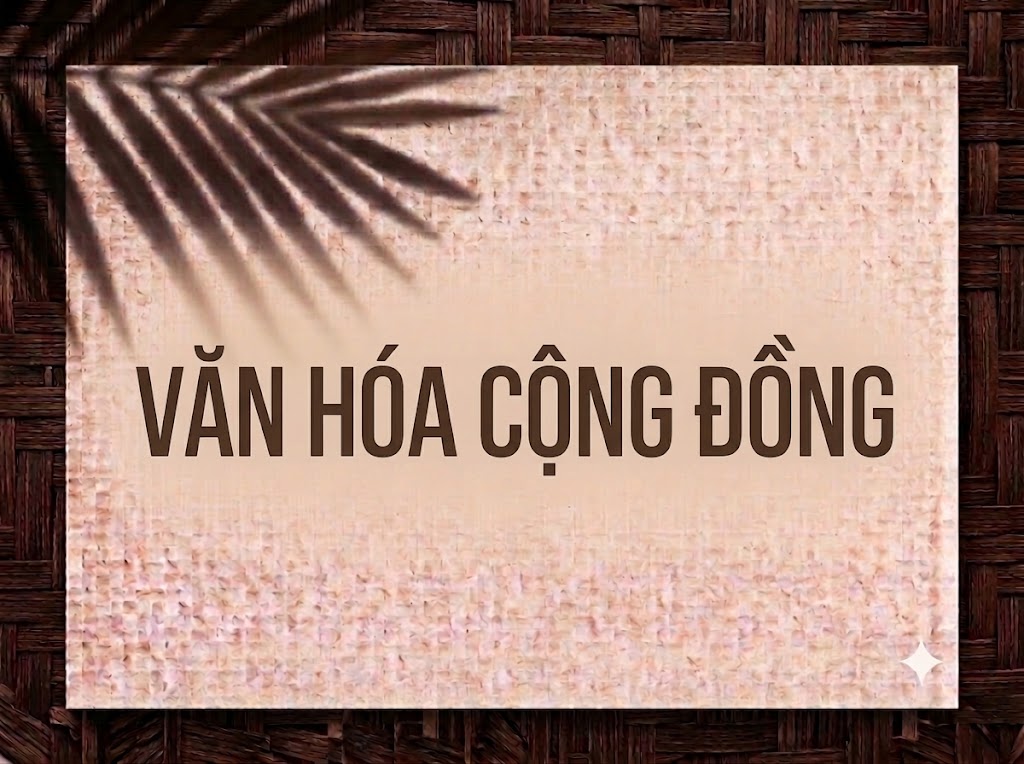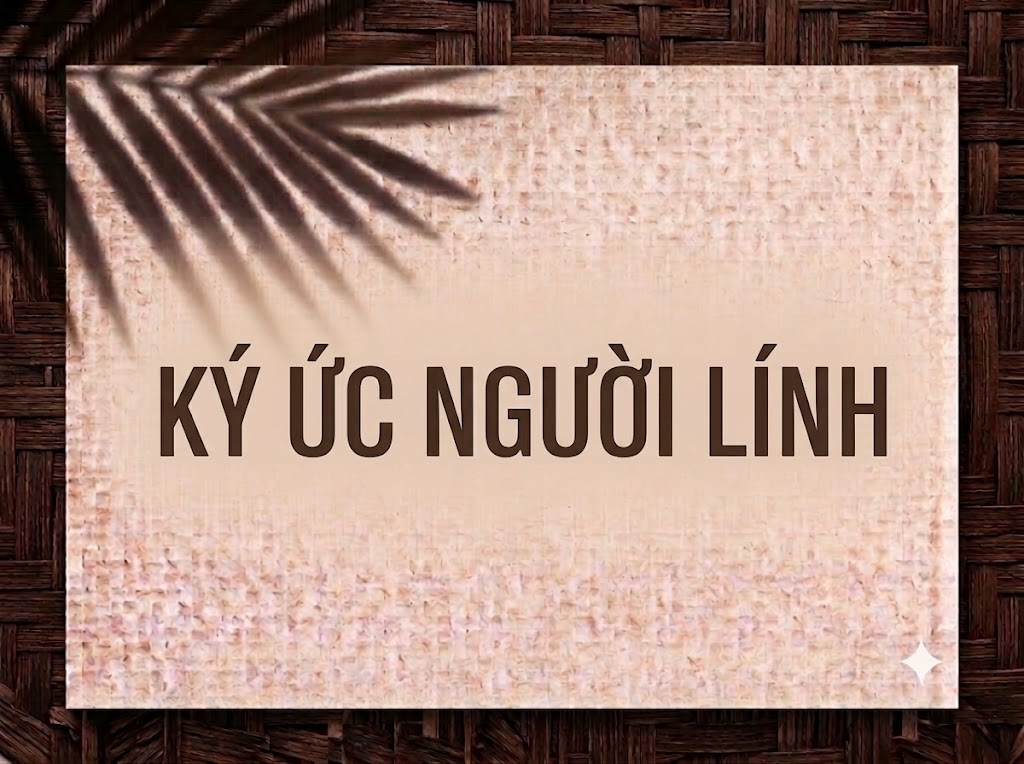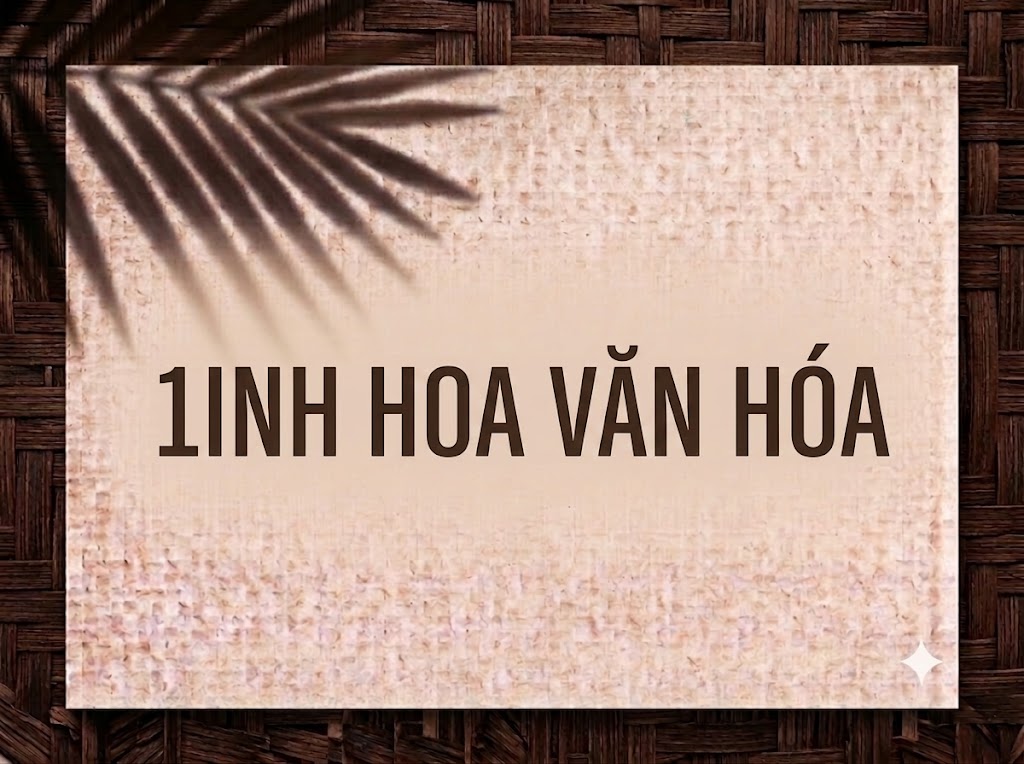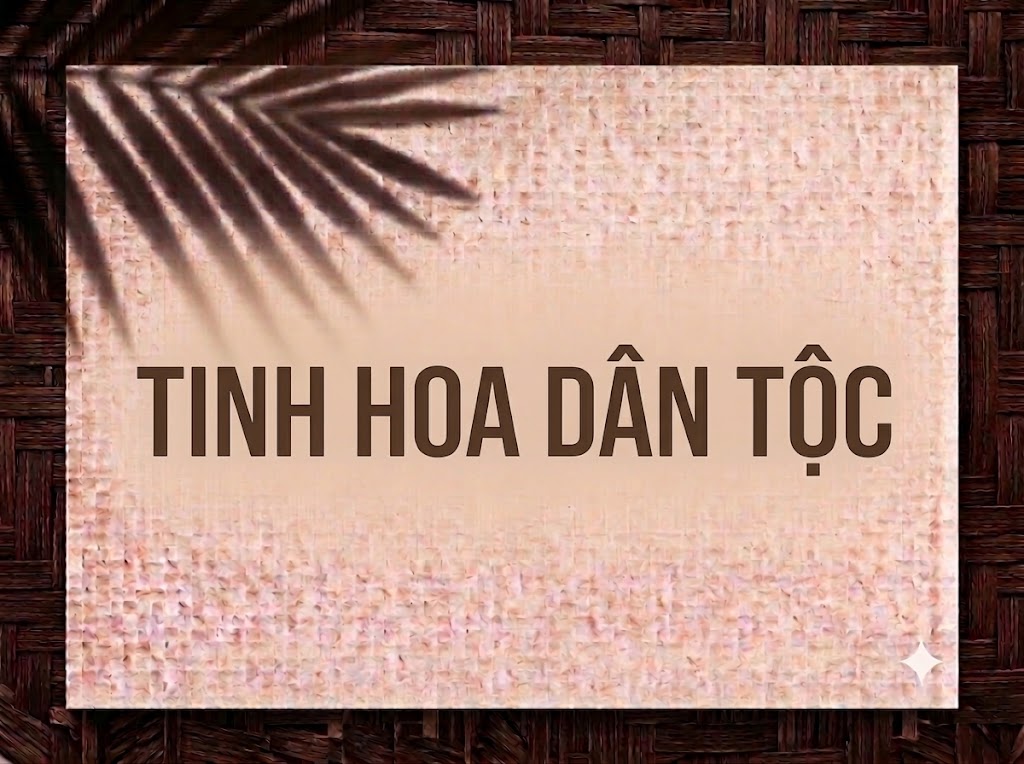
1FTV Subpear
Trong thiết kế đồ họa truyền thông và sáng tạo nội dung số, các phông chữ không chân (sans-serif) có phom dáng nén gọn (condensed) luôn là công cụ đắc lực để giải quyết bài toán không gian. Việc chèn những câu tiêu đề dài vào khung hình hẹp mà vẫn đảm bảo độ rõ ràng, không bị tràn viền đòi hỏi một kiểu chữ vừa thuôn dài, vừa dễ đọc.
Nếu bạn đang tìm kiếm một phông chữ hiển thị hiện đại, thân thiện, sở hữu phom dáng gọn gàng để làm tiêu đề video ngắn, banner quảng cáo hay ảnh thu nhỏ YouTube, font 1FTV Subpear chính là sự lựa chọn rất đáng cân nhắc.
Giới thiệu về font 1FTV Subpear
Font 1FTV Subpear là bộ chữ hiển thị không chân được thiết kế theo tỷ lệ nén vừa phải, mang phong cách hiện đại, tinh gọn và tối ưu hóa tối đa cho các giao diện hiển thị kỹ thuật số:
Tên phông chữ: 1FTV Subpear
Nhờ nền tảng kỹ thuật chỉn chu, phông chữ đem lại khả năng hiển thị mượt mà trên mọi độ phân giải. Bạn có thể tự tin phóng lớn chữ trên các phần mềm thiết kế đồ họa chuyên nghiệp hay ứng dụng dựng phim di động mà không lo gặp tình trạng vỡ nét hay răng cưa.
Đặc điểm nổi bật của phong cách thiết kế Subpear
Sức hút thị giác của font 1FTV Subpear đến từ cấu trúc nén gọn tinh tế kết hợp với đường nét rành mạch, dễ nhìn:
Phom dáng condensed tối ưu diện tích: Chiều ngang ký tự được bóp gọn nhẹ nhàng, giúp bạn dễ dàng xếp trọn những câu giật tít dài hay slogan nhiều từ vào không gian hẹp mà vẫn giữ được kích thước chữ lớn, nổi bật.
Nét chữ rành mạch và thân thiện: Đường nét đồng đều, cấu trúc khung chữ đứng dáng cùng khoảng trống nội tại thông thoáng giúp các từ khi đứng cạnh nhau tạo thành một khối thị giác vô cùng ngăn nắp và dễ chịu.
Hỗ trợ chữ hoa và chữ thường đồng bộ: Khác với các dòng phông display chỉ có chữ in hoa, Subpear tích hợp đầy đủ hệ thống chữ hoa và chữ thường, cho phép bạn phân tầng nội dung chính phụ vô cùng tự nhiên.
Để phông chữ vận hành mượt mà trên cả hệ điều hành Windows lẫn macOS, phiên bản 1FTV Subpear đã được tinh chỉnh kỹ lưỡng về các thông số nội tại:
Khoảng cách giữa các chữ (kerning) và độ giãn dòng được tính toán chuẩn xác, giúp các ký tự dáng nén khi đứng gần nhau không bị dính nét hay gây ngột ngạt khi nhìn.
Tích hợp trọn vẹn bộ chữ cái hoa – thường, dãy chữ số 0-9 phom dáng gọn gàng cùng hệ thống ký tự đặc biệt, dấu câu thông dụng.
Bản Việt hóa chuẩn chỉnh giúp bạn hoàn toàn yên tâm thiết kế các văn bản tiếng Việt có dấu phức tạp mà không gặp lỗi nhảy font hay mất ký tự.
Hình ảnh demo thực tế của font 1FTV Subpear
Khả năng hiển thị của phông chữ này được tối ưu rất tốt trên nhiều tỷ lệ kích thước khác nhau:
Kích thước nhỏ (12pt – 24pt): Nhờ cấu trúc nét ngay ngắn và khoảng hở nội tại rõ ràng, các khối chữ thường và dãy số vẫn hiển thị sắc nét, cực kỳ dễ đọc trên màn hình di động.
Kích thước lớn (36pt – 72pt): Đây là đất diễn lý tưởng nhất để 1FTV Subpear phô diễn sự rành mạch, hiện đại và phom dáng nén gọn ấn tượng, tạo tác động thị giác mạnh mẽ cho các dòng tiêu đề chính.
Ứng dụng trong thiết kế đồ họa và làm video
Sở hữu nét cá tính tinh gọn và linh hoạt, font 1FTV Subpear mở ra không gian ứng dụng phong phú:
Video ngắn (TikTok, Reels, Shorts): Dáng chữ nén gọn rất ăn nhập với khung hình đứng tỷ lệ 9:16, giúp bạn thoải mái chèn các câu tiêu đề hay phụ đề giật tít ở đầu video mà không lo tràn viền hay che khuất chủ thể.
Ảnh thu nhỏ YouTube (Thumbnail): Lựa chọn tuyệt vời cho các kênh làm nội dung chia sẻ kiến thức, review công nghệ, vlog đời sống hoặc thời trang nhờ độ nhận diện trực diện từ xa.
Banner e-commerce và Poster sự kiện: Hoàn hảo cho các poster chương trình khuyến mãi, banner giới thiệu sản phẩm hay các chiến dịch truyền thông cần truyền tải nhiều thông tin.
Nhận diện thương hiệu cá tính: Thích hợp làm logo dạng chữ khối, nhãn mác bao bì sản phẩm hoặc in ấn thiết kế trên áo thun cho các thương hiệu trẻ trung, năng động.